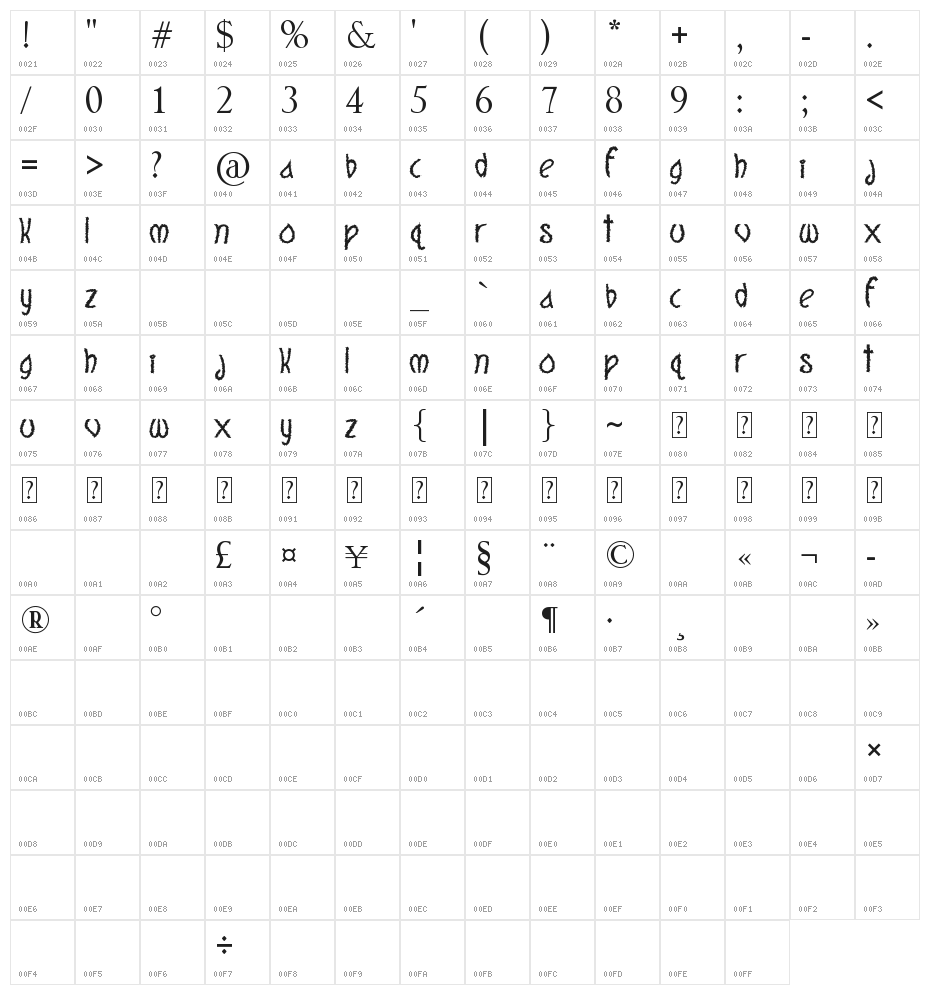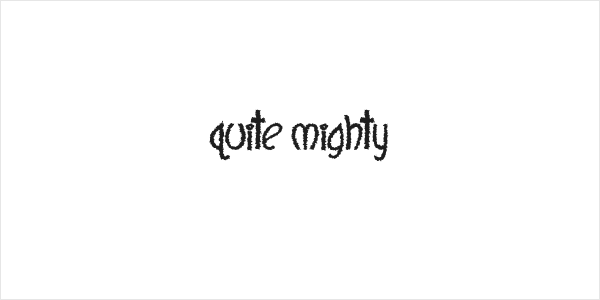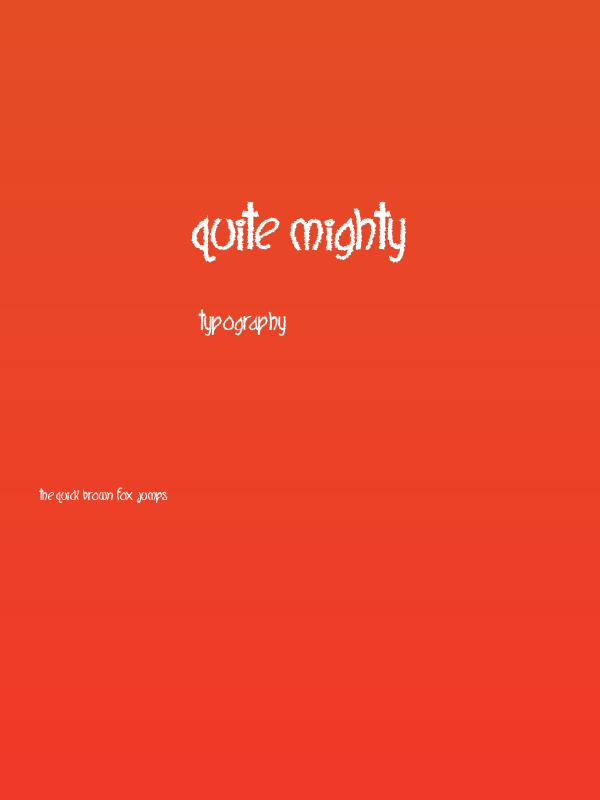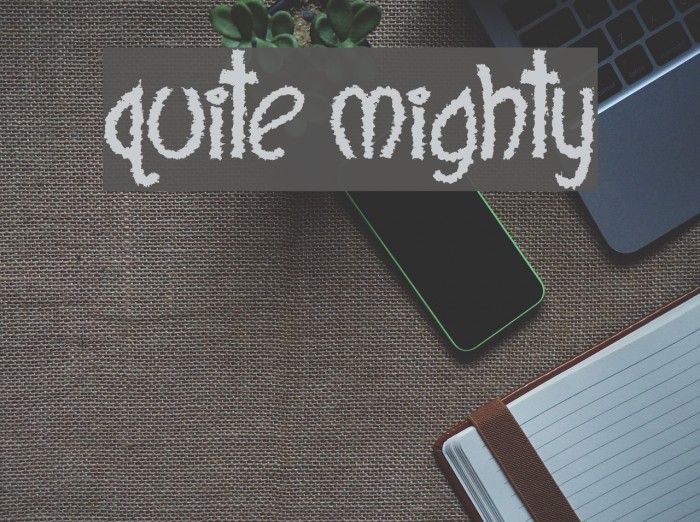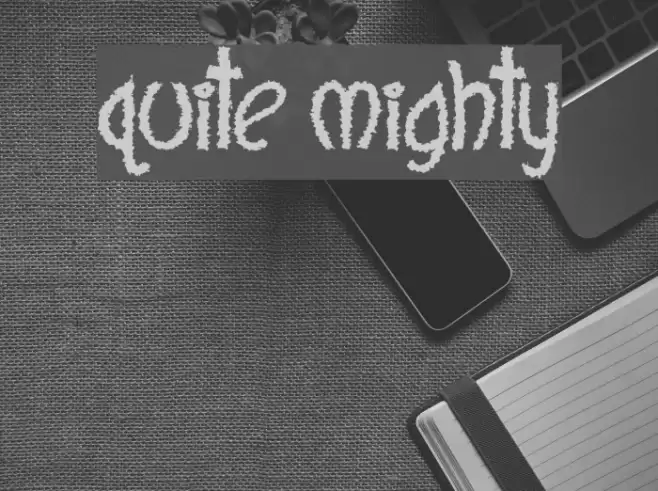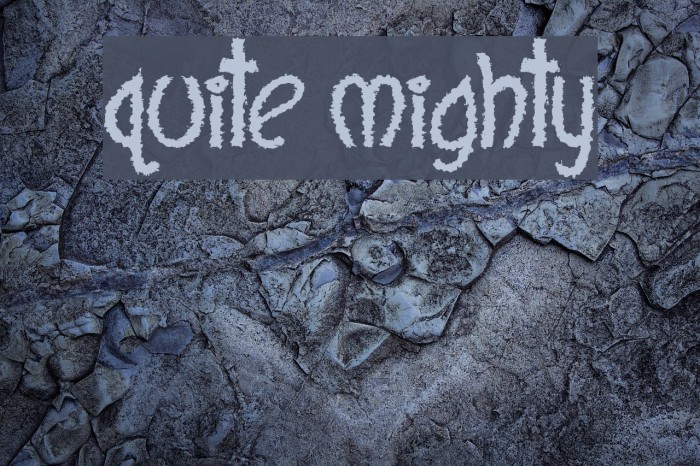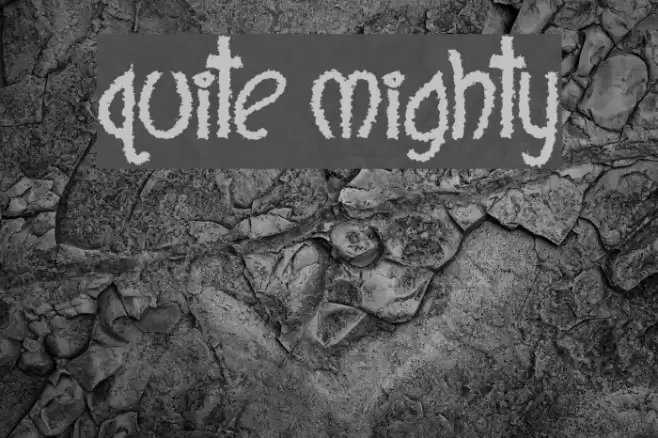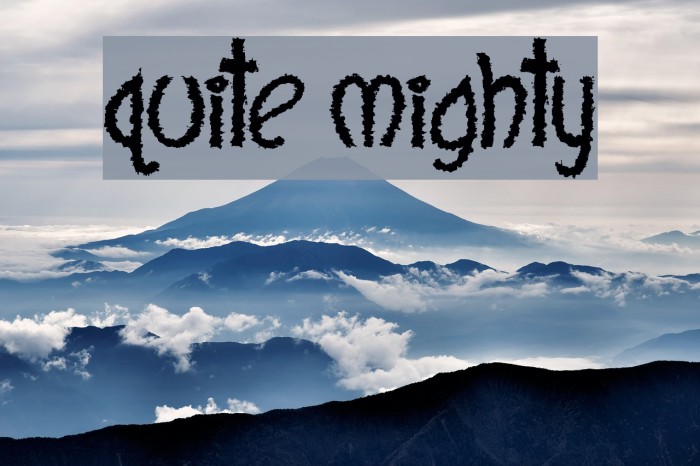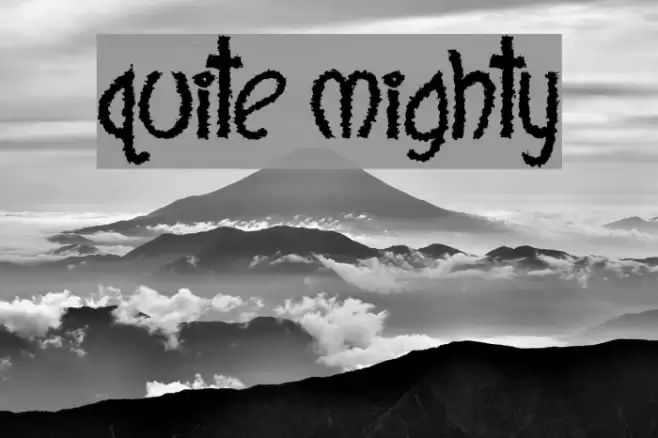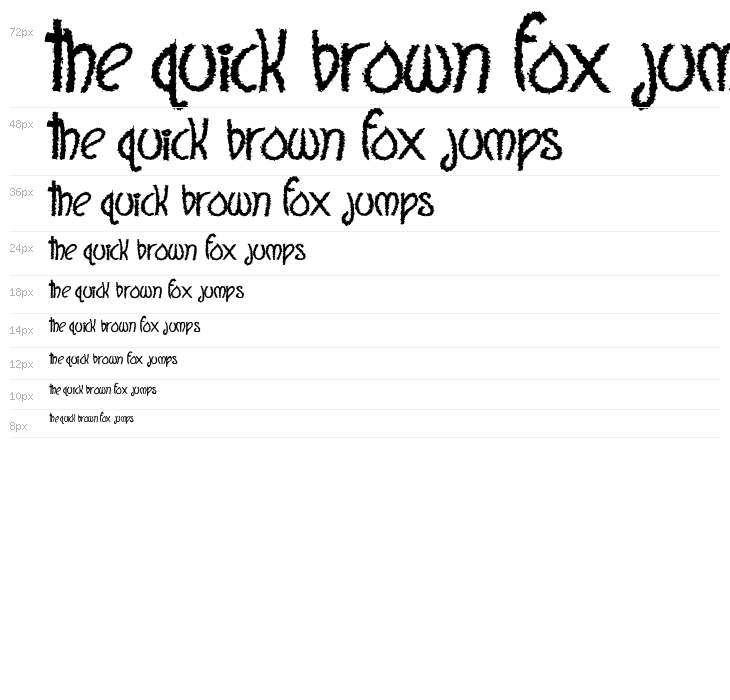
Quite Mighty Font
| Progetti proposti | Ideal for creative projects such as posters, invitations, or branding that require a playful and artistic touch. |